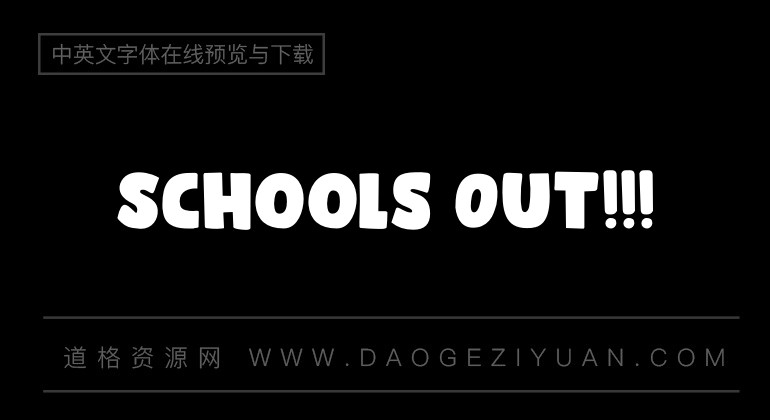
Schools Out!!!
Schools Out!!! 字体是一款卡通式的字体,由美国设计师Aaron Amaral设计,它采用了一种非常小巧的字体,具有鲜明的视觉效果,在字体中还保留了一些细节,比如圆形括号,以及突出的字母,使得它看起来更加有趣。Schools Out!!!字体可以用于各种卡通、漫画和其他类型的设计,有助于增加设计的趣味性和可读性,是一款非常有趣的字体。
Schools Out!!!是一款非常不错的手写艺术字体,具有很好的视觉感,适合于文化类的宣传设计、商业类品牌的广告和产品包装设计以及个性化文字排版等较多场景。
Schools Out!!!字符映射图